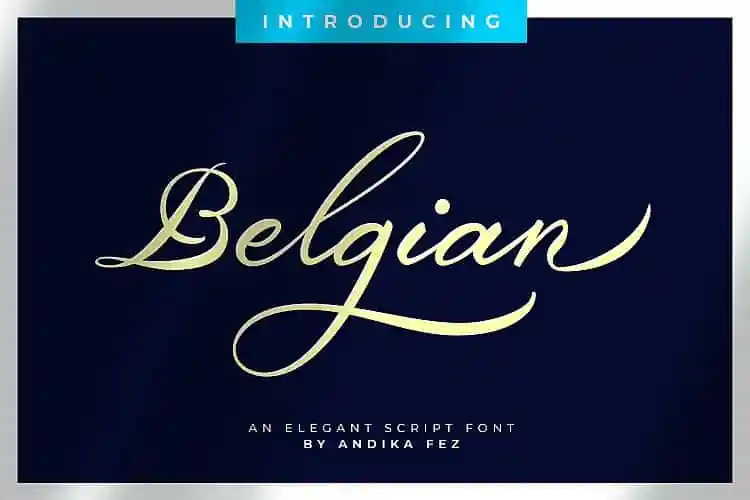
Belgian Signature Font – Download Grátis
Introduzimos a nova fonte script elegantemente elegante chamada Belgian Font. Esta fonte moderna do xilográfico é perfeita para estilos de marca, convites de casamento e cartas, etiquetas e muito mais. Através da inclusão das características OpenType, o Belgian Signature oferece uma ampla gama de opções que permitem aos designers jogar com as fontes de forma livre. Esta é uma excelente adição para aqueles que desejam dar um toque único e sofisticado a seus projetos. Através do seu design meticuloso, esta fonte é perfeita para criar texturas gráficas impecáveis em aplicações como branding, cartas de casamento e etiquetas. Seja você designer ou criativo, o Belgian Signature Font certamente será uma ferramenta valiosa no seu armário de recursos gráficos.